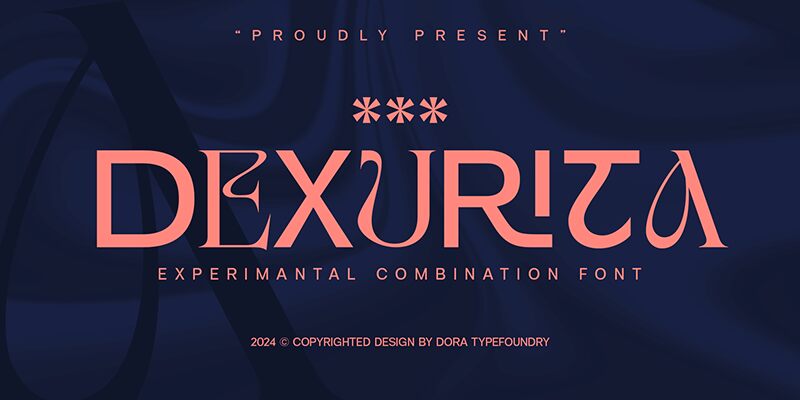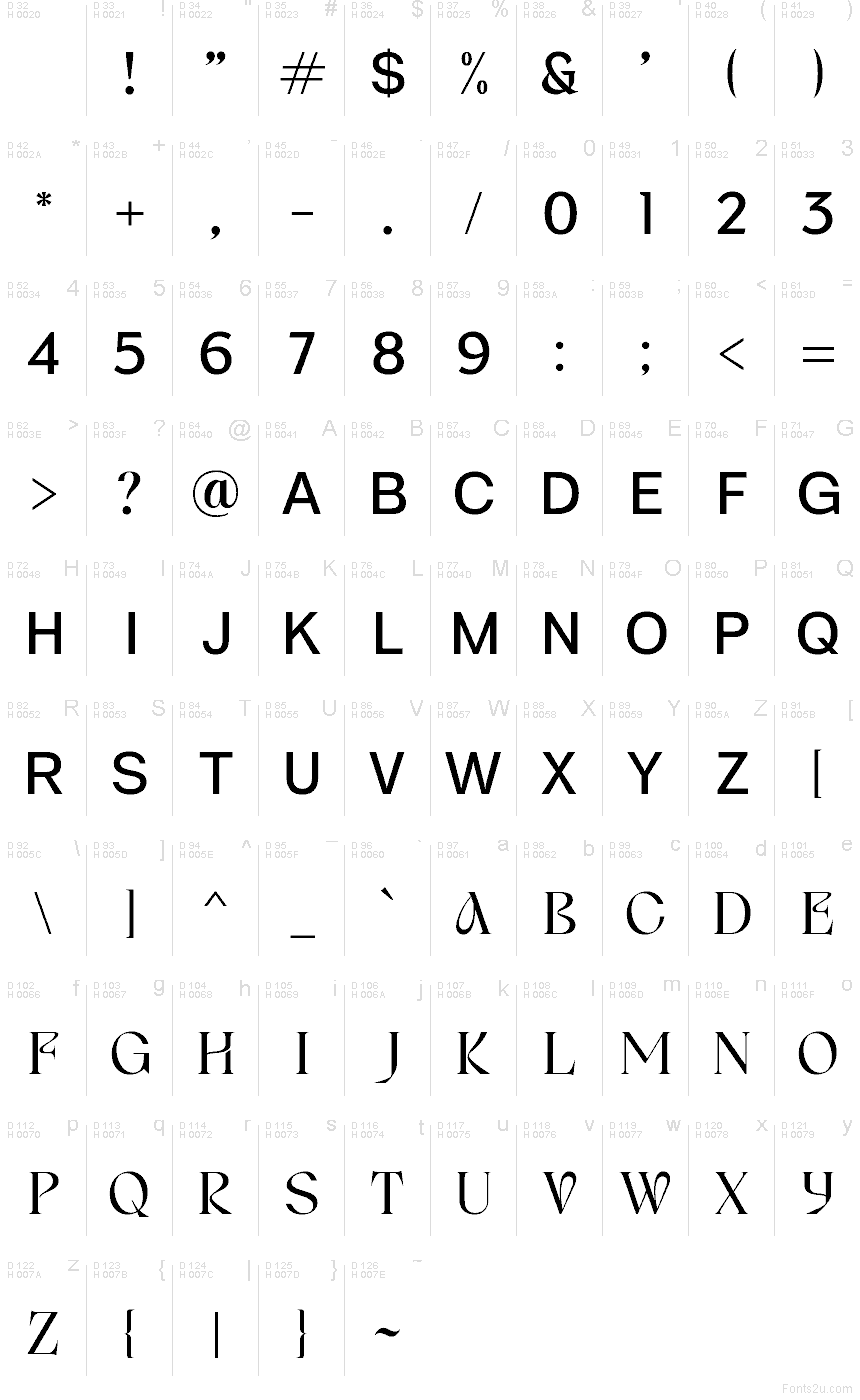
خط Dexurita من Dora Typefoundry هو خط مجاني مزخرف ذو سيريف (زوايا)، يمنحك شعور الأحرف الكلاسيكية المنحوتة في الحجر، ولكن مع لمسات مقطوعة بحدة تشبه ضربة سكين دقيقة. هذه الشقوق المتعمدة تضفي إيقاعاً ودراما على النص دون أن تفقده وضوحه، مما يجعله يبدو جريئاً ومميزاً بلمسة من الأناقة الراقية (كوتور).
استخدام خط Dexurita في أغلفة الكتب، وهويات العلامات التجارية للأزياء، وتغليف العطور، وملصقات الفعاليات، وأغلفة الألبومات، ولوحات المحلات التجارية، والعناوين التحريرية، يمنح نصوصك شخصية فورية وجاذبية خاصة. استخدم Dexurita بأحجام كبيرة لتحقيق أقصى تأثير، وقم بإقرانه بخط sans serif بسيط (مثل خط Grotesk نظيف) للنصوص الفرعية والفقرات - فهذا الخط المجاني يحب التباين الهادئ.